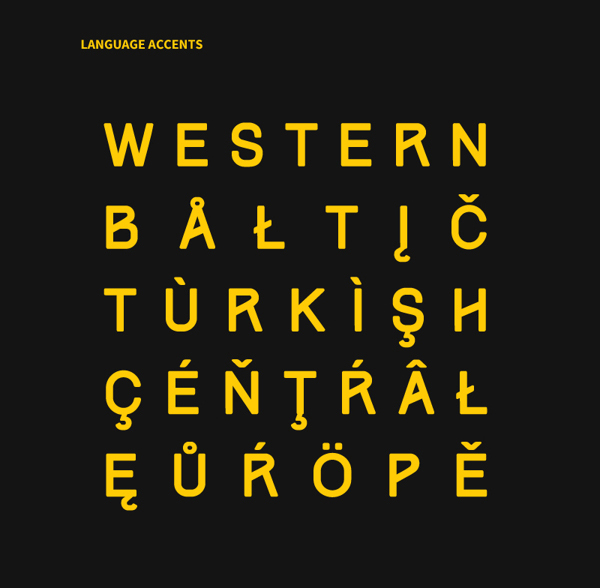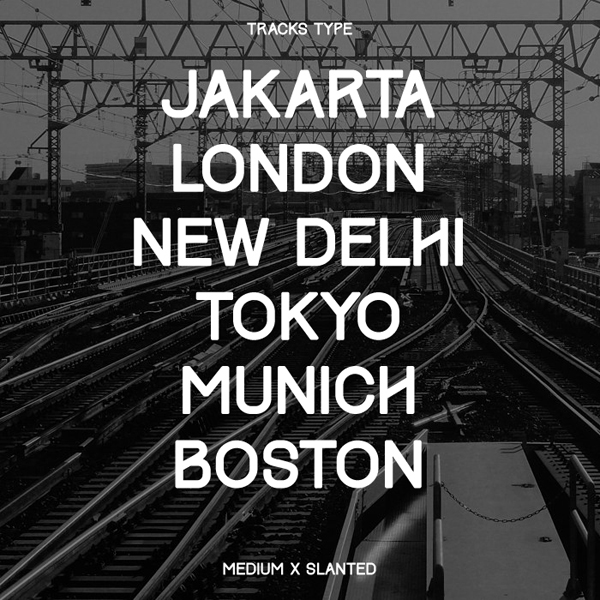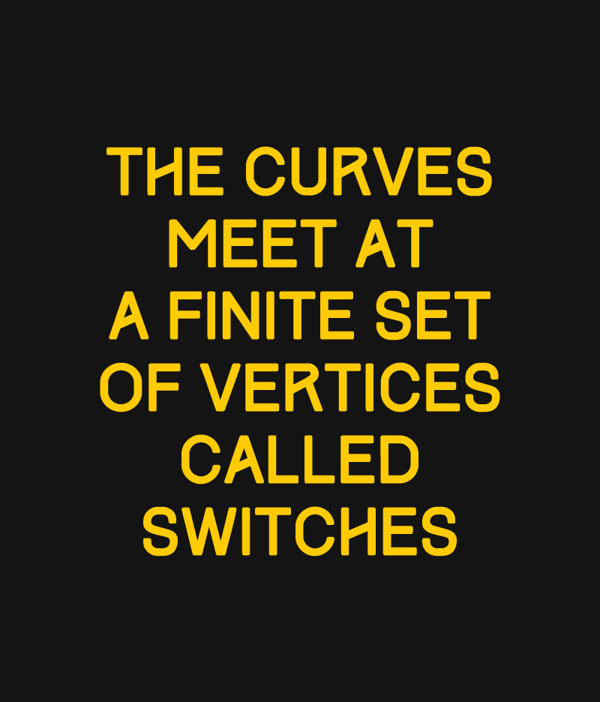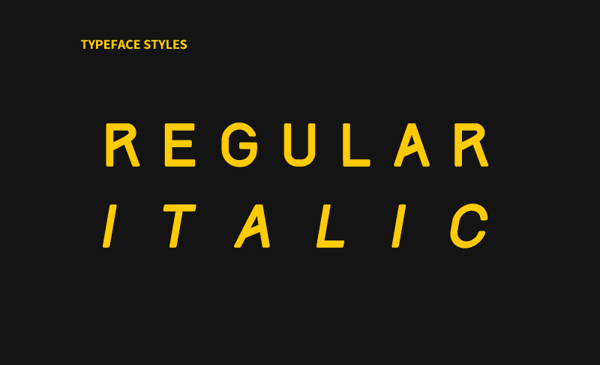
Tracks, una linda tipografía de palo seco inspirada en el mundo del ferrocarril, es disponible mediante libre descarga en la página web de Fontfabric. Se trata de una fuente diseñada en caja alta, tono medio y con su respectiva versión inclinada. Su autor es Gumpita Rahayu, diseñador gráfico freelance residente en Bandung, Indonesia.